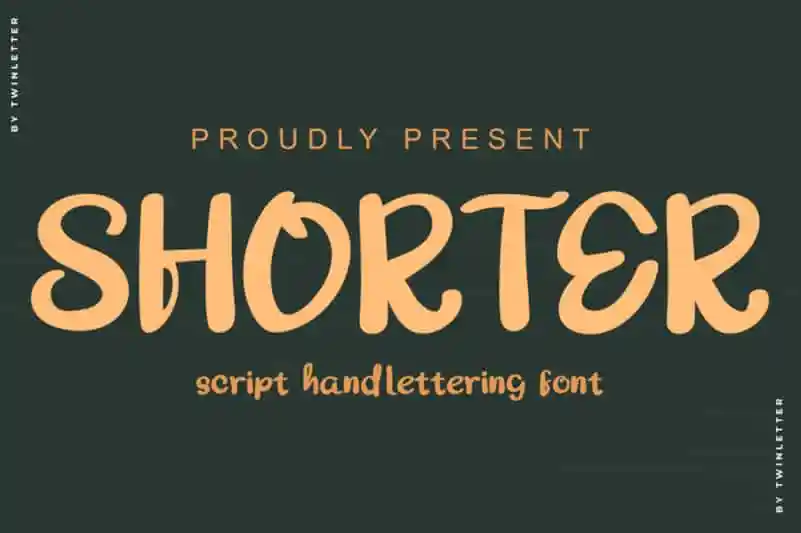
Descubra uma nova opção para seus projetos digitais com a “Shorter Bold Script Font” do designer twinletter. Essa elegante fonte é ideal tanto para escritas de destaque quanto para textos mais informais, se adaptando perfeitamente em qualquer contexto. Através da sua natureza casual e delicada, o “Shorter Bold Script Font” oferece uma aparência confortável e amigável. Suas linhas fortes e acentuadas dão à fonte um tom sóbrio, sem perder seu charme leve e acessível. Perfeito para usos em backgrounds complicados ou como headline destacada, o “Shorter Bold Script Font” é uma opção versátil e moderna que se encaixa perfeitamente com a sua necessidade. Seja você designer gráfico, ilustrador ou qualquer profissional de mídia digital, essa fonte é um excelente complemento para seu trabalho. Tente inovar em seus projetos digitais hoje mesmo! Experimente “Shorter Bold Script Font” e explore o poder dessa fonte única e versátil.